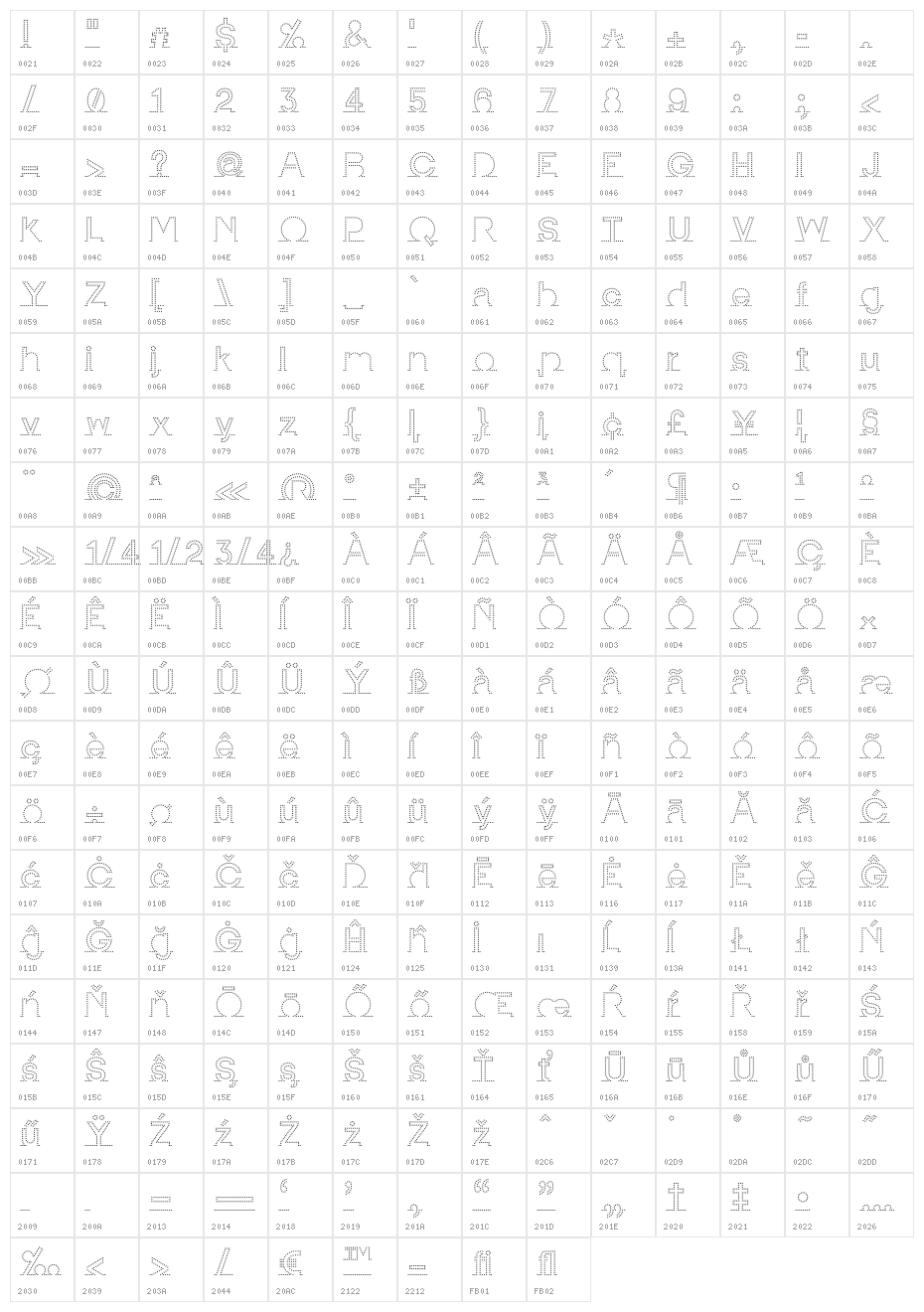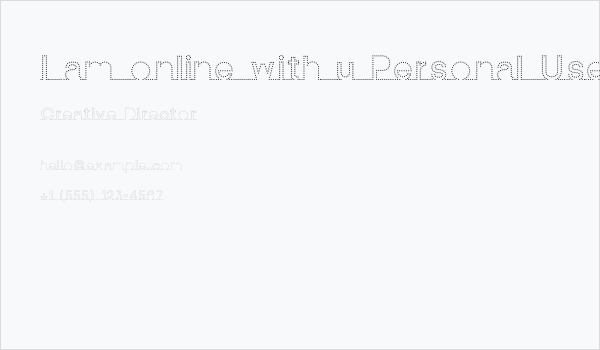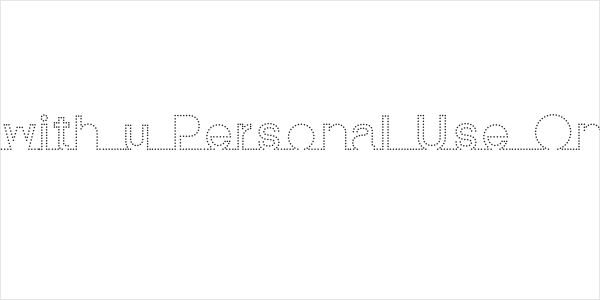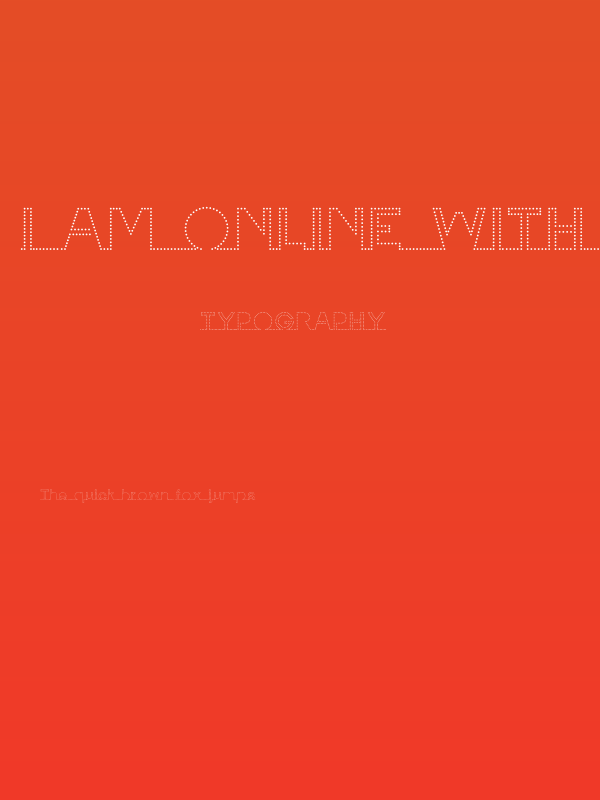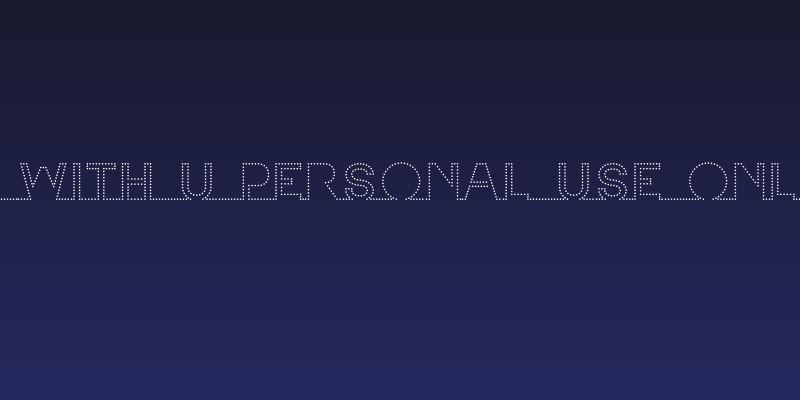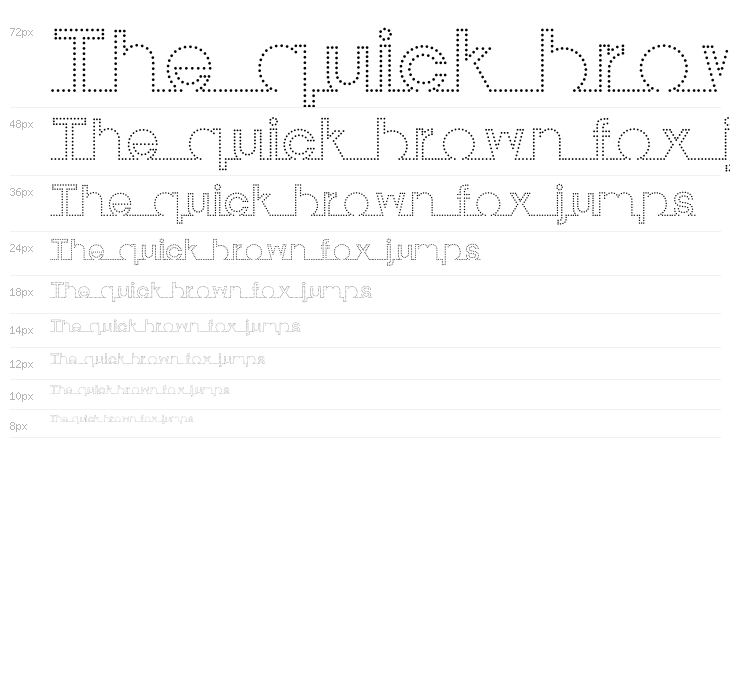
I am online with u Personal Use Only Dotted 2 Font
| Caso d'uso | Headlines, Logos, Creative projects |
| Progetti proposti | Ideal for creative projects such as posters, invitations, and branding materials where a unique and eye-catching font is desired. |